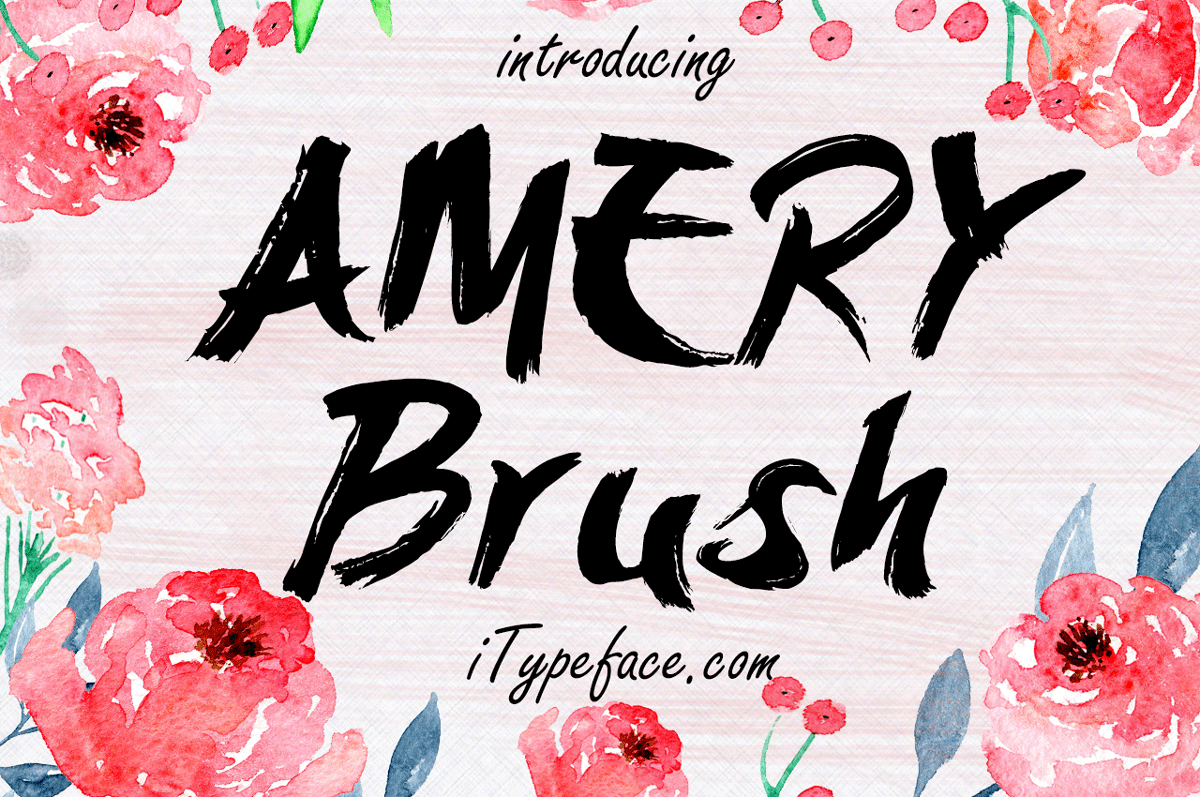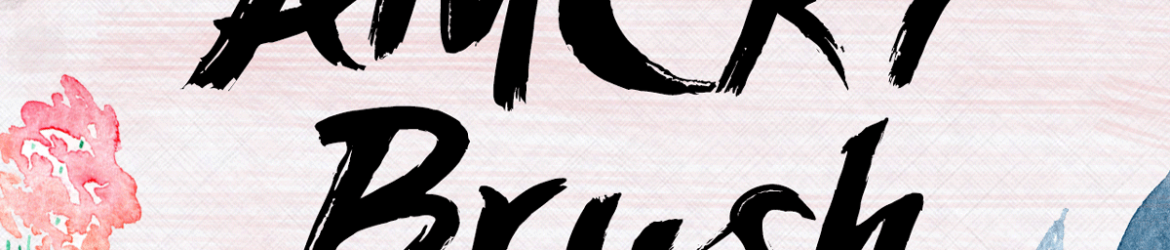
A Amery Brush é uma fonte com traços suaves e aparência vintage, criada a mão por um artesão do tipoletro. Suas formas brutais remetem à pintura de sinais antigos, oferecendo tanto letras maiúsculas quanto minúsculas, números e símbolos. Esta fonte está perfeitamente adaptada para diversos usos gráficos, incluindo embalagens de papelaria, logotipos e muito mais. Seu uso é simplificado no Adobe Illustrator ou Photoshop. A Amery Brush vem em uma variedade completa que complementa a estética vintage do estilo da fonte, permitindo aos designers uma ampla gama de possibilidades para criar gráficos impecáveis. Para quem busca uma fonte que expressa elegância através de seu charcovel robusto e moderno, a Amery Brush é um excelente escolha.